드로잉을 통한 발견_사이러스 하이스미스 Cyrus Highsmith
사이러스 하이스미스(Cyrus Highsmith)는 미국 보스턴에 자리한 타입페이스 개발회사 폰트 뷰로(Font Bureau)에서 신규 서체 개발을 맡고 있는 시니어 디자이너이다. 2001년 프린트 매거진(Print Magazine) 뉴 비주얼 아티스트 리뷰(New Visual Artist Review)에 소개되며 알려지기 시작한 그는 프렌자(Prensa), 스테인리스(Stainless), 안테나(Antenna) 등의 서체로 이제는 실력과 명성을 함께 지닌 디자이너로 인정받고 있다.
그는 타입페이스 디자인에 있어서 무엇보다 드로잉의 중요성을 강조한다. 심지어 드로잉을 평생의 열정이라고 말하기까지 하는데, 이는 드로잉을 통해 타입페이스 디자인을 차별화된 자신만의 시각으로 바라볼 수 있기 때문이라고 한다. 좋은 디자이너가 되기 위한 덕목은 무엇인가에 대한 질문에도 그는 단순히 이렇게 대답한다. “Draw, draw, draw…”
드로잉으로 시작하여 드로잉으로 완성되는 그의 디자인과 디자인 철학을 들어보자.
국내 독자들에게 간단한 자기 소개 부탁드립니다.
로드 아일랜드 디자인 스쿨(Rhode Island School of Design)를 졸업하고, 1997년부터 지금까지 폰트 뷰로(Font Bureau, Inc)에서 일하고 있습니다. 현재는 그곳에서 신규 타입페이스 개발을 맡고 있는 시니어 디자이너로, 로드 아일랜드 디자인 스쿨에서 타이포그래피와 문자드로잉을 가르치고 있기도 합니다. 주요 개발 타입페이스로는 프렌자(Prensa), 스테인리스(Stainless), 안테나(Antenna) 등이 있습니다.
타입페이스 디자이너가 된 과정은 어떠했나요?
사실 전 처음부터 타입페이스 디자인을 공부했던 것은 아닙니다. 한때 미술을 공부하기도 했고, 로드 아일랜드 디자인 스쿨에 재학 시 그땐 그곳에 타입페이스 관련 학과도 없었죠. 학교에서 그래픽 디자인을 전공하면서 스스로 관심을 가지게 된 분야가 타입페이스 디자인입니다. 당시 수많은 타입페이스를 드로잉하며 실력을 키웠고, 때때로 폰트 뷰로에 찾아가 제가 드로잉한 타입페이스 디자인을 보여주곤 했었죠. 결국 졸업 후 바로 폰트 뷰로에 들어가게 되었고, 데이빗 버로우(David Berlow), 매튜 카터(Matthew Carter), 토비아스 페레-존스(Tobias Frere-Jones)등의 어시스턴스로 2~3년간 실무를 배우고, 그 이후에는 저만의 프로젝트를 수행하기 시작했습니다.
자신이 개발한 타입페이스 중 대중들에게 가장 잘 알려진 것은 무엇이고, 그 이유는 무엇이라고 생각하십니까?
아마도 스테인리스(Stainless)일 것입니다. 이 타입페이스가 대중적으로 성공한 이유에 대해서는 딱히 뭐라고 집어 말씀드릴 수가 없습니다. 제가 타입페이스를 만들 때 트렌드를 따르는 것이나 제작 후 대중들에게 어필하는 것에는 솜씨가 그다지 좋지 않기 때문입니다. 누군가에게 유용한 타입페이스는 비슷한 부류의 다른 이들에게도 유용할 것입니다. 그래서 타입페이스를 제작할 때 실제든 가상이든 특정한 클라이언트를 설정하기도 하는데, 스테인리스 경우에는 저명한 출판디자이너를 타겟으로 제작되었죠. 이것이 성공으로 이어지다 보니 다른 수 많은 출판디자이너들에게도 이 타입페이스가 유용하게 쓰여졌나 봅니다.
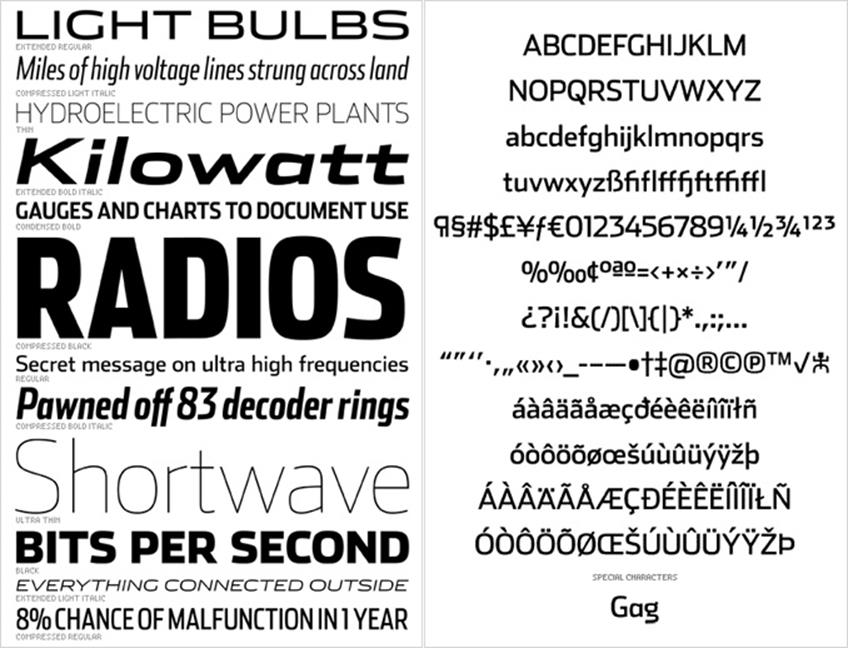
▲ 스테인리스(Stainless), 프리미어 매거진(Premiere magazine)에 사용되기도 했다.
다른 몇 가지 대표 타입페이스들을 독자들에게 소개부탁드립니다.
먼저 산세리프체 스타일의 안테나(Antenna)가 있습니다. 사람들은 제 서체를 통해 신나고 자유로운 특징을 발견하고 기대하는데, 안테나는 여기에 차분함과 신중함을 더해 보다 발전적인 형태를 갖추고 있습니다. 또한 이탤릭체를 포함하여 일곱 종류의 굵기와 네 종류의 폭으로 총 56개의 다양한 스타일을 갖추고 있어 세부적인 작업까지 효율적으로 도와줍니다.
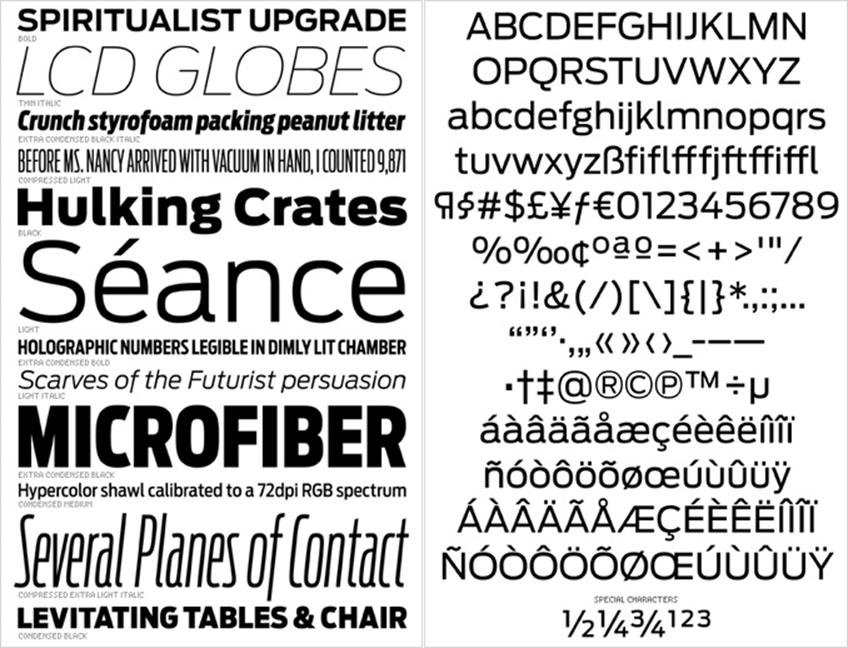
▲ 안테나(Antenna)
또 하나의 대표 타입페이스로는 신문용인 조칼로(Zocalo)입니다. 조칼로는 멕시코 시티의 데일리 신문인 ‘엘 유니버셜(El Universal)’에 쓰인 서체로 본문용과 디스플레이용이 서로 조금 다른 특징을 가지고 있습니다. 본문용은 니콜라스 키스(Nicholas Kis)의 올드 스타일과 천시 그리핀스(Chauncey Griffith)의 전통적인 신문 타입페이스인 ‘아이오닉 No. 5’에서 영감을 얻어 제작된 반면 디스플레이용은 활동적이고 에너지 넘치는 멕시코 시티의 분위기를 한껏 담았습니다.
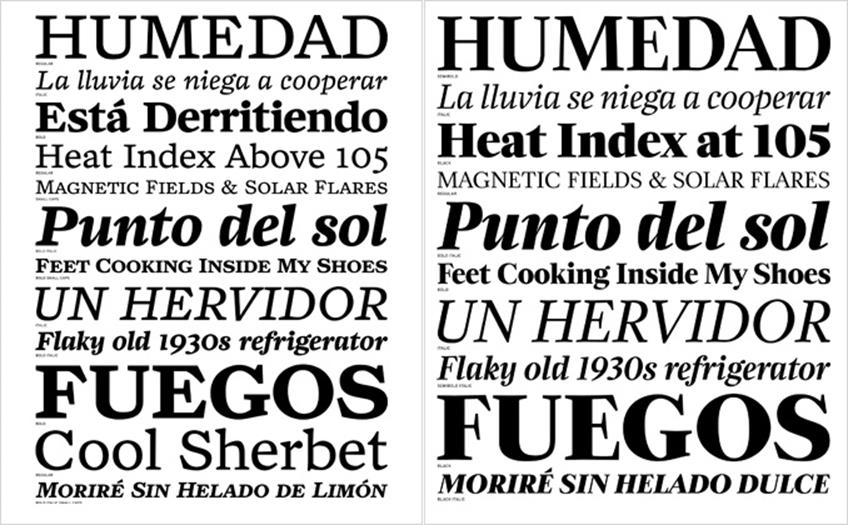
▲ 조칼로(Zocalo) 본문용(좌)과 디스플레이용(우)
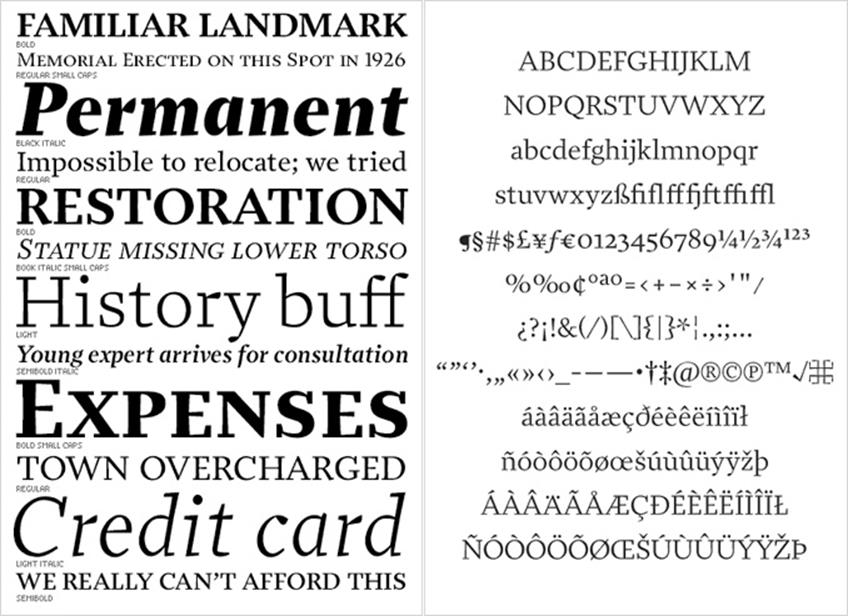
▲ 프렌자(Prensa). 인터뷰에서 언급하지는 않았지만 프렌자 역시 그의 대표적인 타입페이스 중 하나이다. 2002년 국제 타입페이스 공모전인 ‘Bukva:Raz!’의 수상작으로 초기 그의 이름을 알리는데 결정적 역할을 한 타입페이스이기도 하다.
최근에 진행한 프로젝트가 있다면?
최근에 아이비스(Ibis) 시리즈를 발표했습니다. 아이비스는 유스투스 에리히 발바움(Justus Erich Walbaum)의 ‘발바움(Walbaum)’ 과 헤르만 챠프(Hermann Zapf)의 ‘멜리어(Melior)’ 에서 영감을 얻은 것으로 이들 두 타입페이스가 조합한다면 어떤 새로운 스타일이 탄생할 것인가에 대한 호기심을 시작으로 제작된 프로젝트입니다.
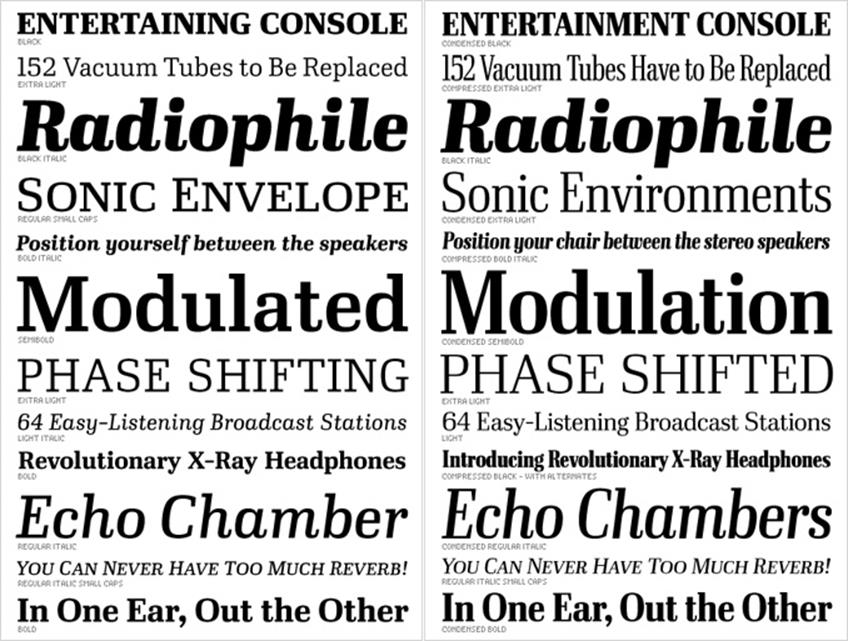
▲ 아이비스(Ibis) 본문용(좌)과 디스플레이용(우)
타입페이스를 제작할 때, 자신만의 작업 스타일이 있나요?
1940년대 라이노타입의 디자이너였던 천스 그리피스(Chauncey Griffith)가 했던 작업 방식을 저만의 스타일로 받아들이고 있습니다. 이 방식은 자간 조절과 문자 드로잉이 동시에 이뤄져야 하는 것이 특징인데, 이는 작업 시간을 아낄 수 있을 뿐만 아니라 드로잉을 하며 문자 내의 공간과 자간의 관계를 끊임없이 일깨워줍니다.
작업 프로세스 면에서는 초반에는 주로 연필로 러프하게 스케치를 하며 아이디어를 꺼내지만, 이후 대부분의 작업은 컴퓨터를 통해 이뤄집니다. 그리고 교정작업에 많은 시간을 투자하는 편인데, 교정을 보기 전에는 꼭 휴식을 취하는 편입니다. 그래야지 생기 있는 눈으로 정확하게 살펴볼 수 있기 때문입니다.
폰트를 만들 때 어떤 소프트웨어를 사용하나요?
사실 저는 지금 사용하고 있는 소프트웨어가 그렇게 마음에 들지 않습니다. 그래서 무엇이라고 언급하기가 꺼림직하네요. 아주 기술적인 차이를 제외하면, 소프트웨어는 디자인 전반에 작은 부분일 뿐이라고 생각합니다.
웹사이트(www.occupant.org)를 보면 스케치북이라는 흥미로운 프로젝트를 볼 수 있는데, 어떤 프로젝트인가요?
어떤 클라이언트를 위한 것이 아닌 저만의 작업을 보여드리는 것입니다. 드로잉을 통해 많은 것들을 생각하고 발견하는 저는 지난 15년 동안 거의 매일 스케치북에 문자뿐 아니라 카툰이나 글, 혹은 일상 속에서 발견한 무엇이든 드로잉을 해왔습니다. 이 작업들은 순수하게 재미와 아이디어를 위한 것이지 아름답게 보여지려는 것은 아닙니다.
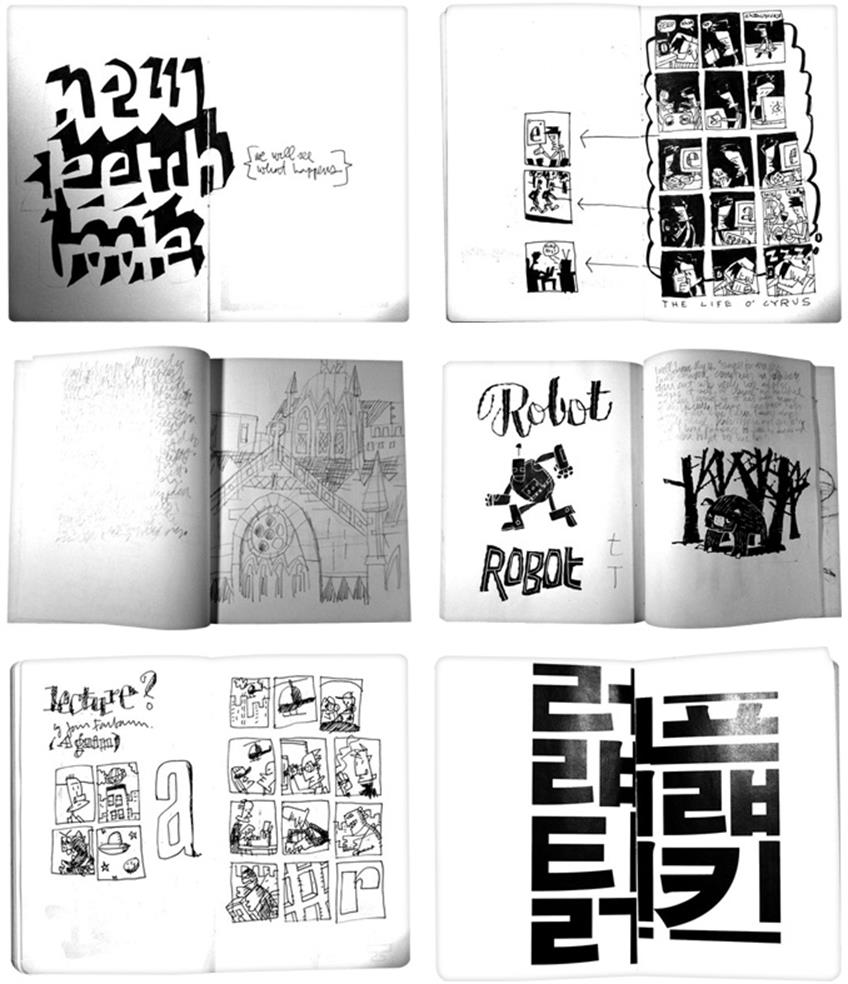
▲ 그의 웹사이트를 방문하면 습작형식의 다양한 드로잉을 엿볼 수 있다.(www.occupant.org). 흥미로운 점은 그의 스케치북 속에서 한글 드로잉도 만나볼 수 있는 데, 그는 한글에 대해 관심이 많다고 한다.
최근 E-book 이나 태블릿 등이 업계의 이슈로 떠오르고 있습니다. 이런 새로운 기기들을 위한 타입페이스 디자인에 대한 견해를 듣고 싶습니다.
본문을 위한 타입페이스를 디자인 할 때, 먼저 해상도에 의한 제약을 받게 됩니다. 무슨 말이냐면, 지면에 인쇄된 경우에는 10포인트의 게라몬드(Geramond)와 카스론(Caslon)의 차이를 쉽게 느낄 수가 있지만 태블릿 스크린에서 동등한 사이즈의 이 폰트들을 보면 그 차이가 분명하지가 않습니다. 차이가 날 만큼 픽셀이 충분하지 못하기 때문이죠. 타입페이스 디자이너로써 이는 매우 맥 빠지는 일입니다. 공들여 제작한 서체가 그 세밀한 디테일적 특성을 충분히 보여줄 수 없으니까요.
그리고 보다 더 안 좋은 상황은 태블릿용 폰트를 만들고 난 후, 그 활용에 있어서 일어나게 됩니다. 태블릿 스크린은 정해진 사이즈의 특성상 때로는 세로단이 너무 좁은 레이아웃이나 줄 사이 공간이 너무 넓게 할애되도록 강요하기도 하는 등 조판상의 많은 제약들이 타입페이스의 역할을 상당히 축소시키고 있습니다. 태블릿이나 E-book은 이제 앞으로를 이끌어갈 선진 IT기술인 것은 확실하지만, 타입페이스 디자인 부분에서는 아직 원시적인 수준으로 이는 타입페이스 디자이너, 그래픽 디자이너, 퍼블리셔, 태블릿 제조업자들이 함께 고민해야 할 문제라고 생각합니다.
자신에게 영향을 끼친 타입페이스 디자이너가 있다면?
대부분 일을 함께하는 동료들에게 영향을 많이 받습니다. 오랜 경험과 숙련된 기술을 가진 데이빗 버를로우(David Berlow)와 매튜 카터(Matthew Carter), 그리고 자기만의 신선한 관점과 열정을 가진 신진 디자이너인 데이빗 조나단 로스( David Jonathan Ross)까지 모두에게 많은 도움을 받고 있습니다.
좋은 타입페이스 디자인이란 무엇일까요?
매거진 헤드라인에 쓰이던, 소설 속 본문에 사용되던, 좋은 타입페이스란 자신의 용도가 무엇인지 명확하게 알고, 특별하게 쓰여지는 것이라고 생각합니다. 왜냐하면 타입페이스 디자인은 글꼴 자체가 아닌 그것에 의해 형성된 일련의 맥락을 통해 평가할 수 있기 때문입니다. 또한 좋은 타입페이스는 어떤 이야기가 말하고자 하는 의미를 전달할 때, 더욱 극적이거나, 미묘하게 혹은 차분하게 그 의미를 더욱 부각시켜 줄 수 있도록 도움이 되어야 합니다
마지막으로 앞으로의 계획과 타입페이스 디자인을 공부하는 이들에게 해주실 조언이 있다면?
먼저 지금 학생들을 위한 타이포그래피 도서를 집필하고 있습니다. 2011년에는 완성될 것입니다. 타입페이스 디자인을 공부하는 학생들, 혹은 이제 막 시작한 디자이너들에게 해줄 수 있는 조언은 ‘드로잉이 가장 중요하다’ 입니다.